与号
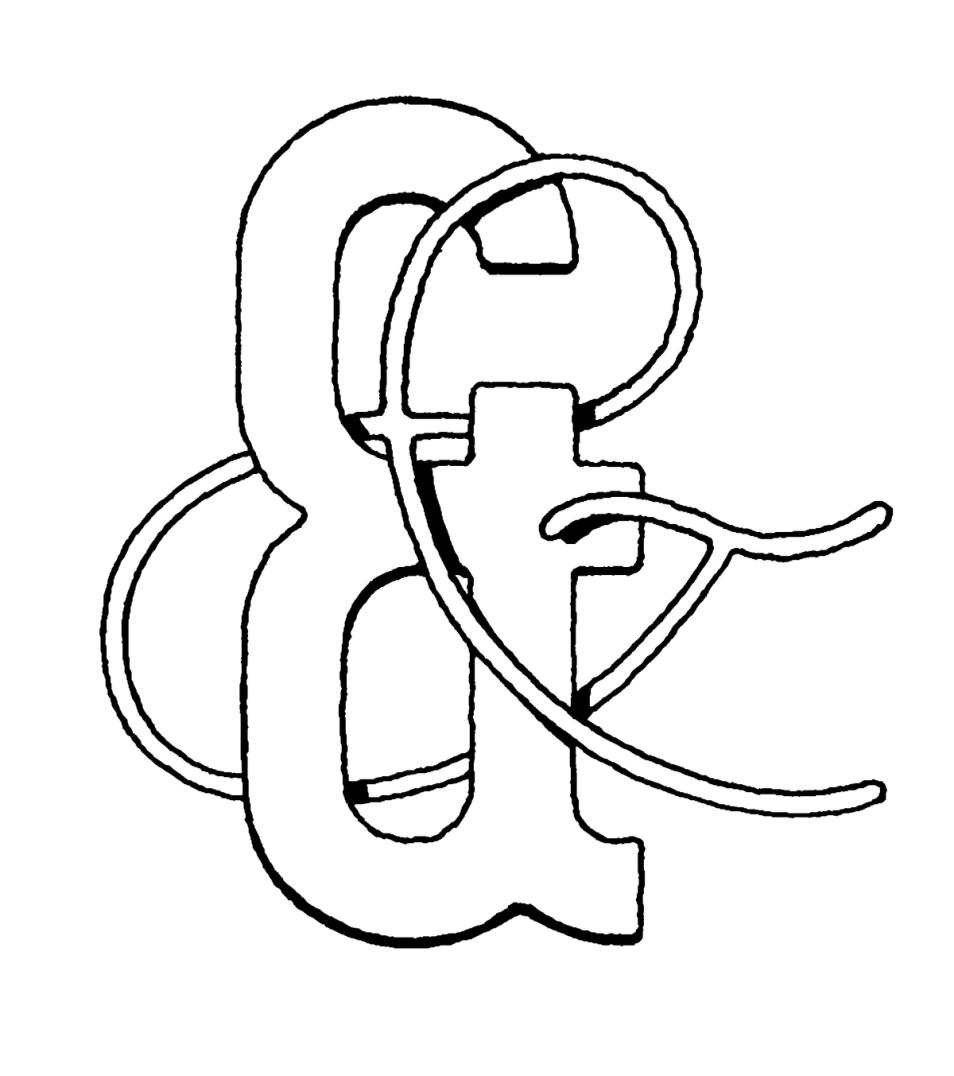
与号为一个字符,用于标题、公司或品牌名称中的组合词,以代替 “and”。
在欧洲中世纪,书籍主要用于传播宗教文本。因此,即使在古腾堡于 1450 年发明金属活字印刷术之后,大多数书籍仍以拉丁文书写。字母 e 和 t(et 在拉丁语中意为 “与”)被频繁使用,以至于字冲雕刻师将这两个字母组合成一个字母 et,先是作为合字,后来单独成为一个字符。
从字母 e 和 t 的直接组合到更为华丽的变体,与号有很多的设计可能性。它的顶部通常与大写字母或数字对齐,以保持足够的易认性。
在标题或品牌中,与号大多数情况下作为一种装饰性的附加,代替单词 “and”(或其他语言中的同义词)。在正文中最好使用单词 “and”。
AMPERSAND: U+0026